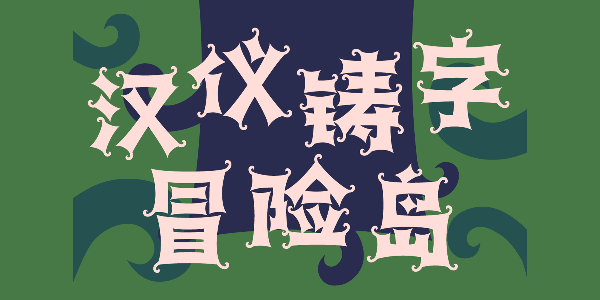
汉仪铸字冒险岛
奇幻 / 神秘 / 活泼 / 趣味 / 卡通
汉仪铸字冒险岛 | 字体特征
“汉仪铸字冒险岛”是汉仪旗下“铸字社工作室”设计的一款装饰性标题字体。无论是冒险岛屿、漂流旅行、奇幻游戏、神秘场景、趣味动植物、还是天马行空想象力的展现,都可以通过这款字体来呈现。
汉仪铸字冒险岛 | 字面灵活多变
整体字形方正敦实,字面宽窄多变、特点丰富,突破了汉字方块的感觉。这款字体追求变化有节奏感的结构,又保持了字之间重心的统一性,使字体排版出来活泼有趣又有序。
通过对字框的变宽处理,使字间距更均衡,易读性强。
汉仪铸字冒险岛 | 笔画风格明显
在不影响整体识别度的前提下,部分笔画使用了“减笔”的设定,整体更加简洁又富有特色,充满艺术性。
笔画粗壮,中部内敛。两端尖锐突出、棱角分明,静中有动。给人锋利、灵敏、紧张和危险的视觉感受。
汉仪铸字冒险岛 | 装饰角可爱活泼
起笔收笔有简洁不对称的弧形装饰角。既增强了字体的灵动性,又带来多种奇幻的联想:是丛林中肆意生长的藤蔓植物?是蜥蜴俏皮卷曲的尾巴?是异域的铁艺装饰?还是海盗船长的铁钩?
汉仪铸字冒险岛 | 中西文匹配
“汉仪铸字冒险岛”的西文字母整体看方正刚直,没有明显的弧形字形。与中文设计相同,运用粗壮、中部内敛、两端尖锐突出的笔画,加上灵活多变的装饰元素,刚中有柔略显俏皮。
汉仪铸字冒险岛 | 排版效果
汉仪铸字冒险岛 | 字体样张